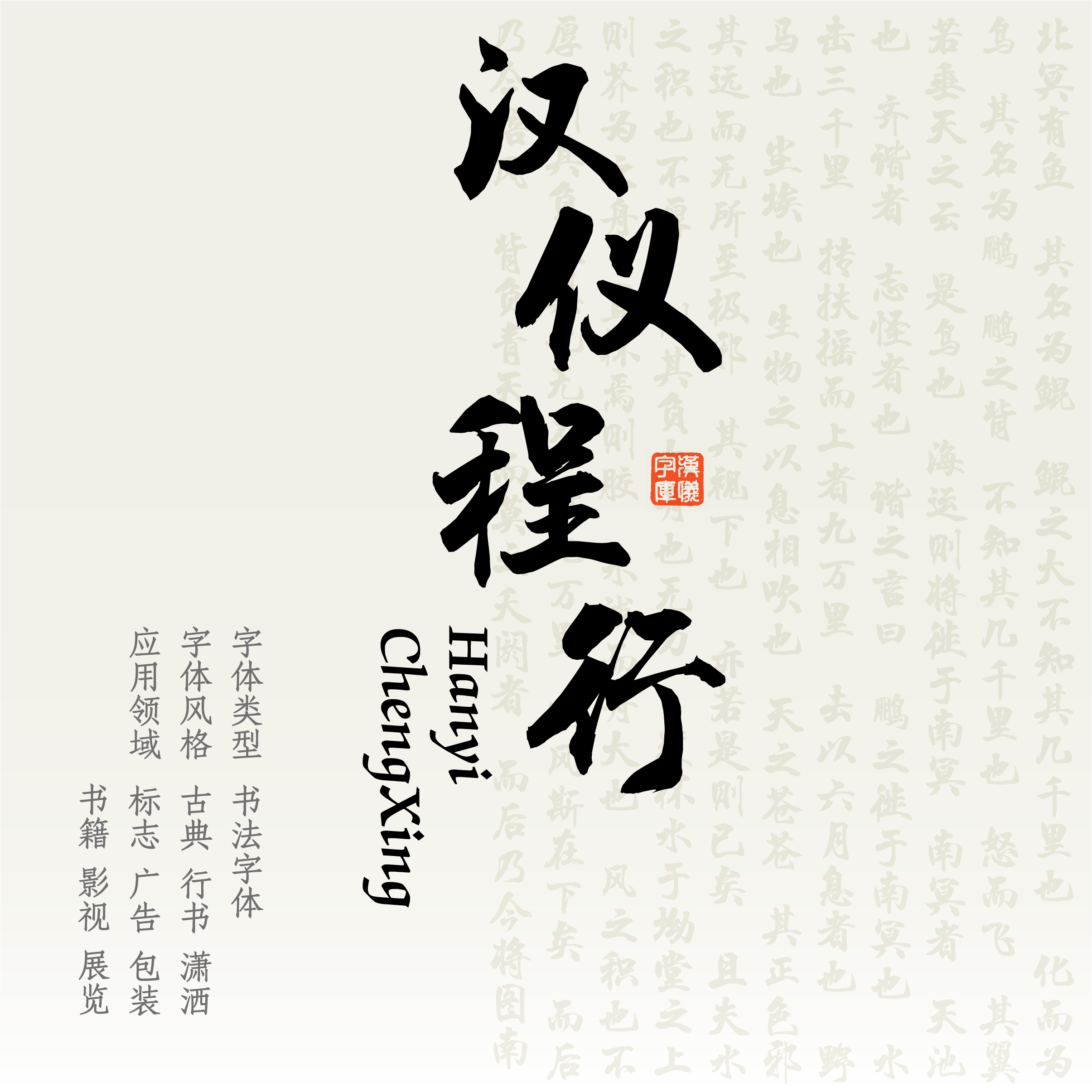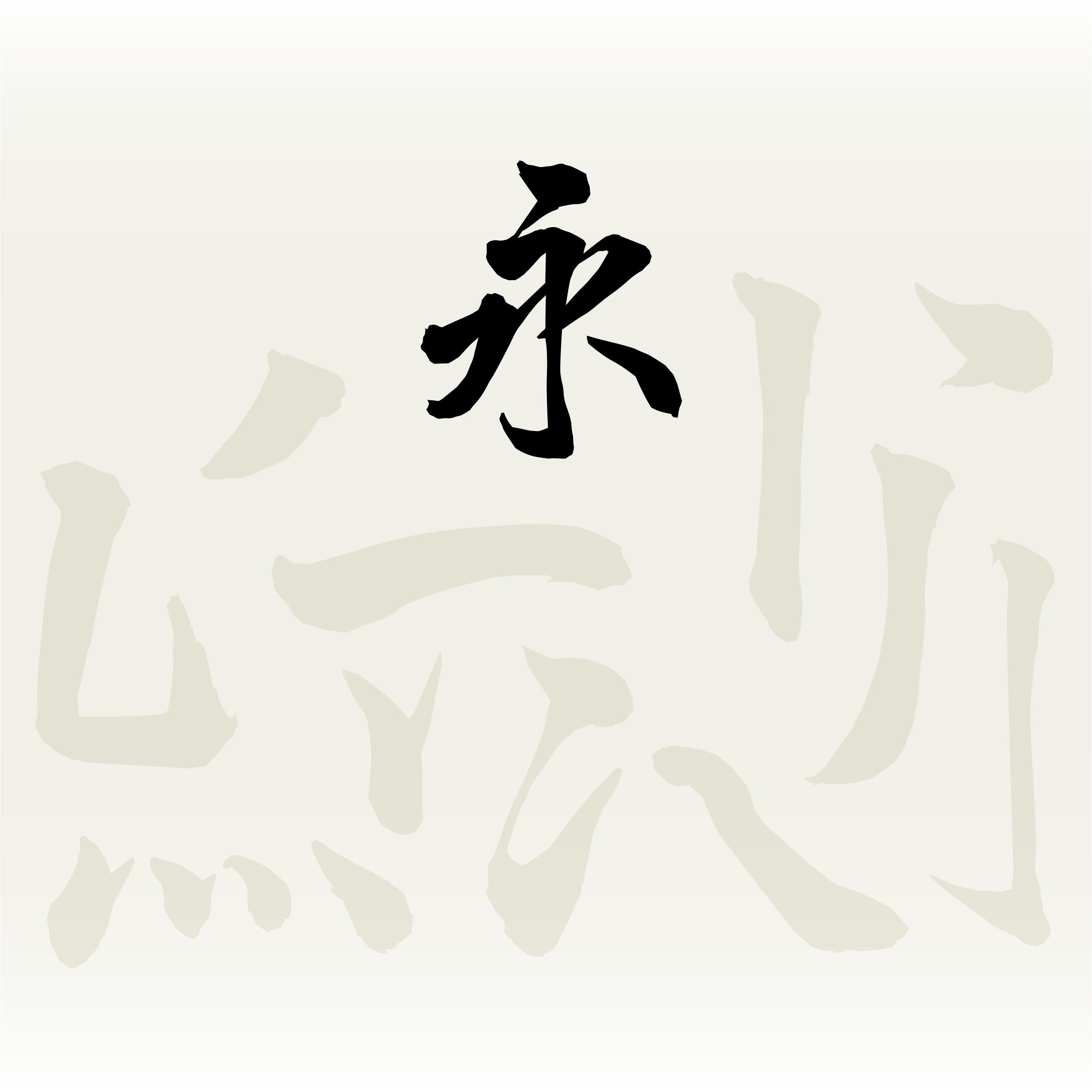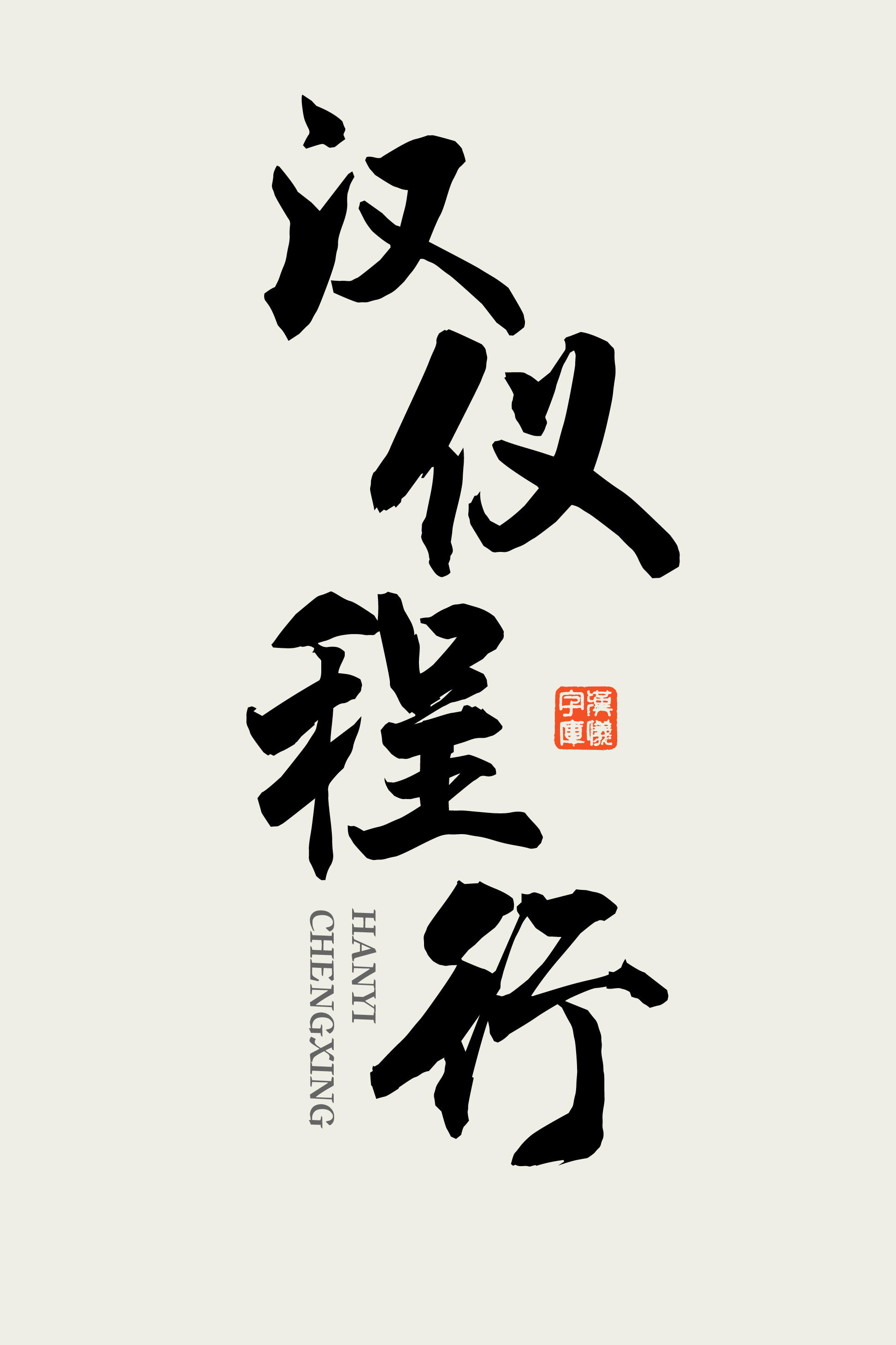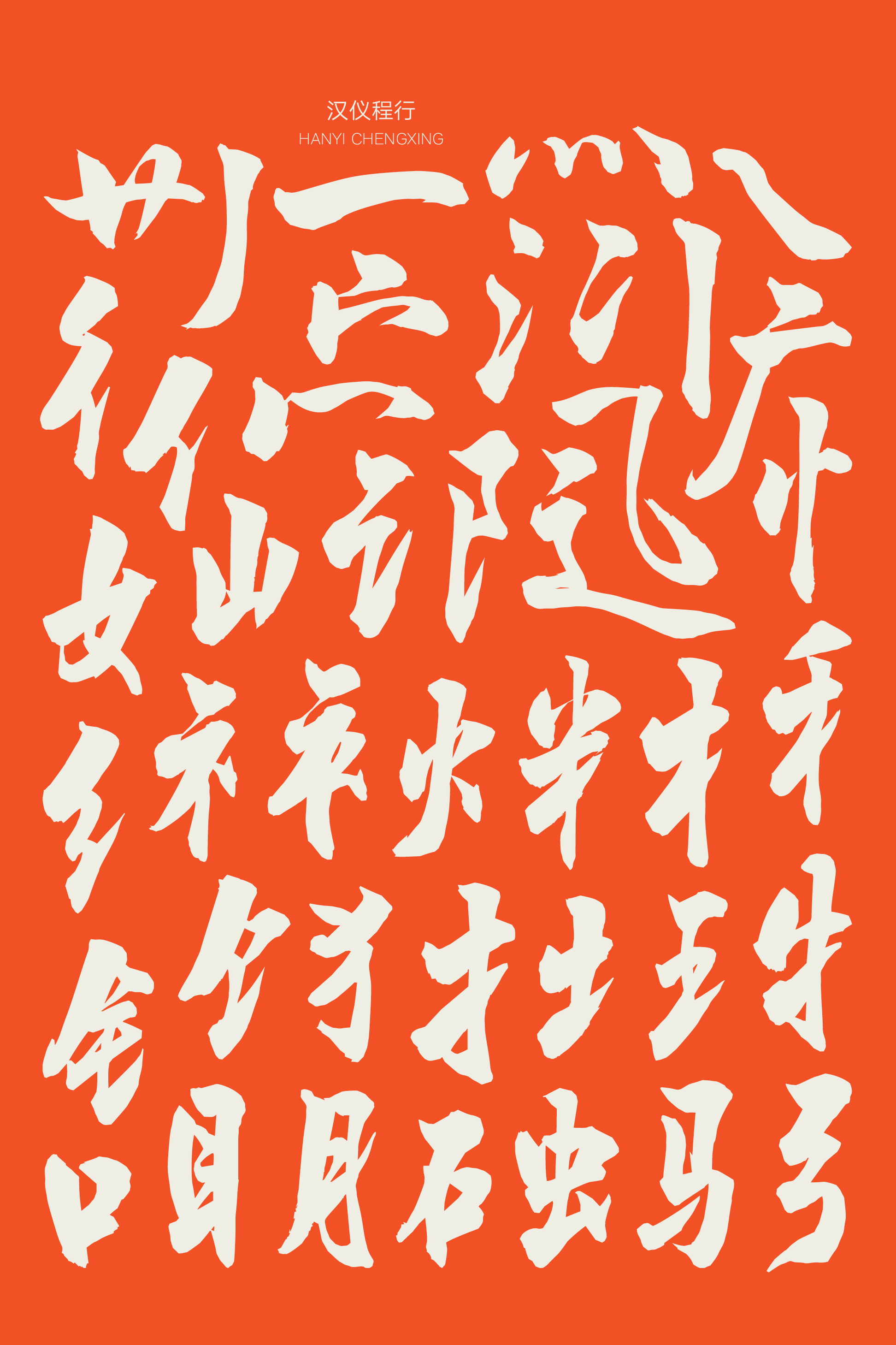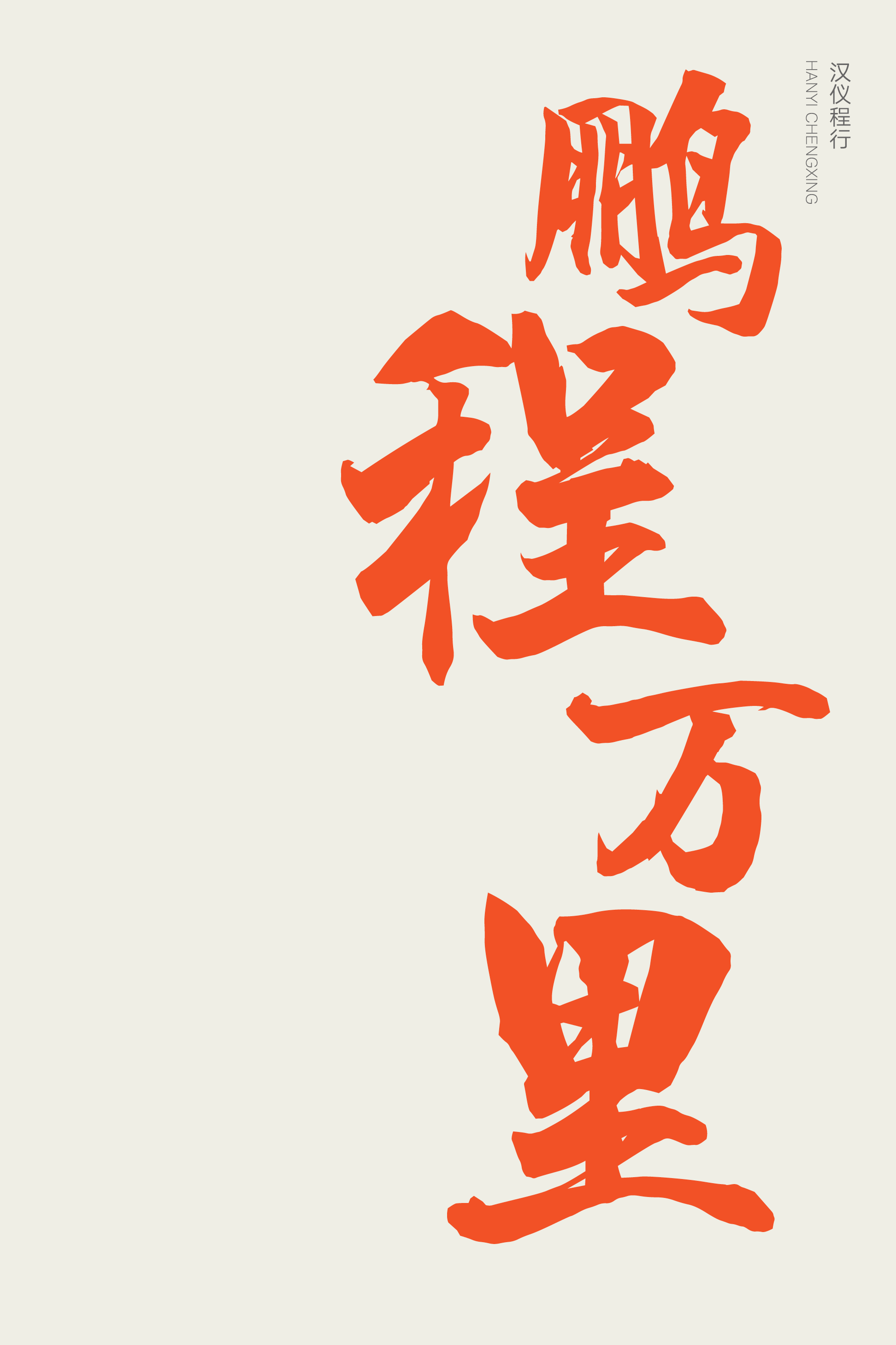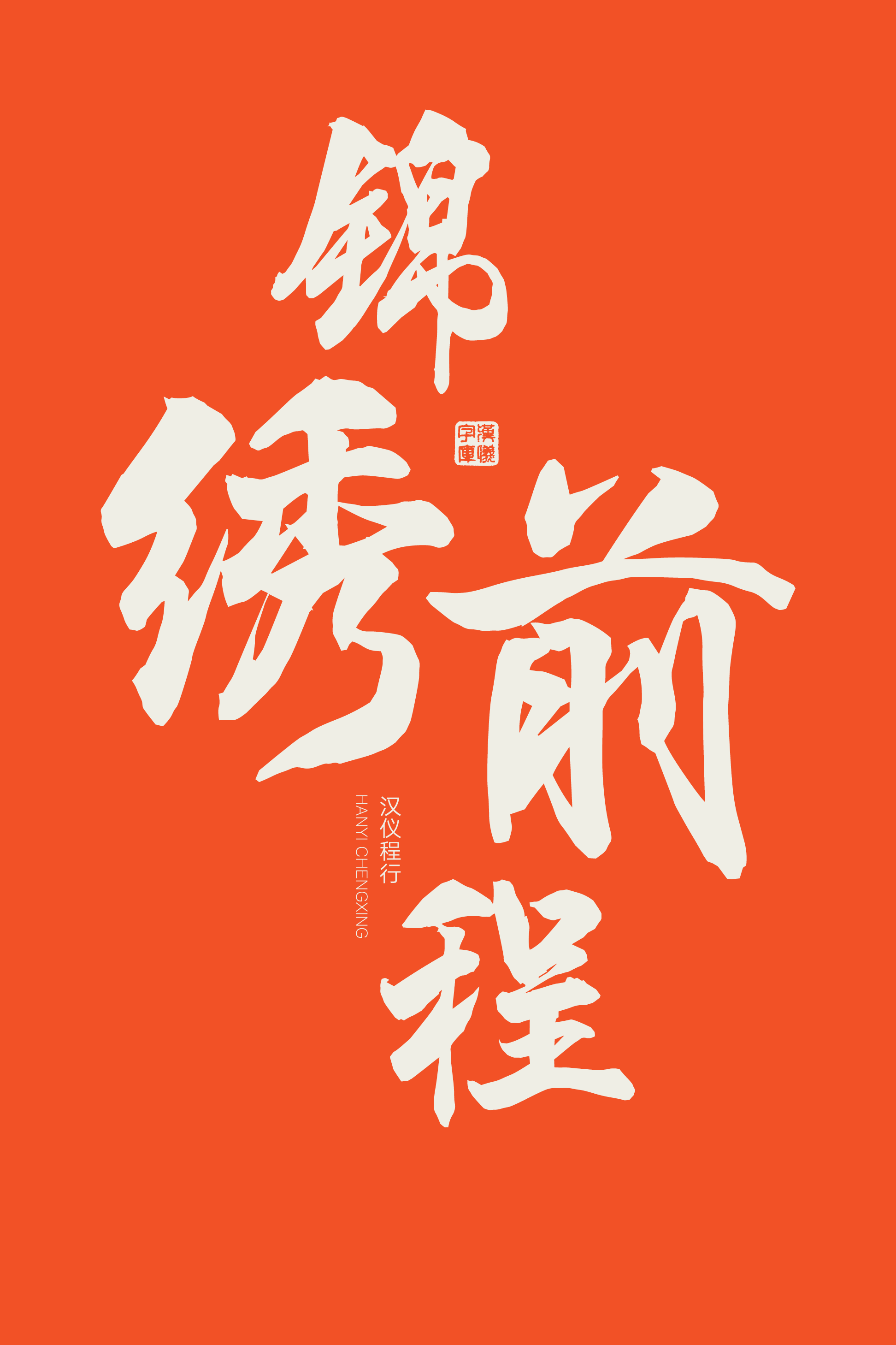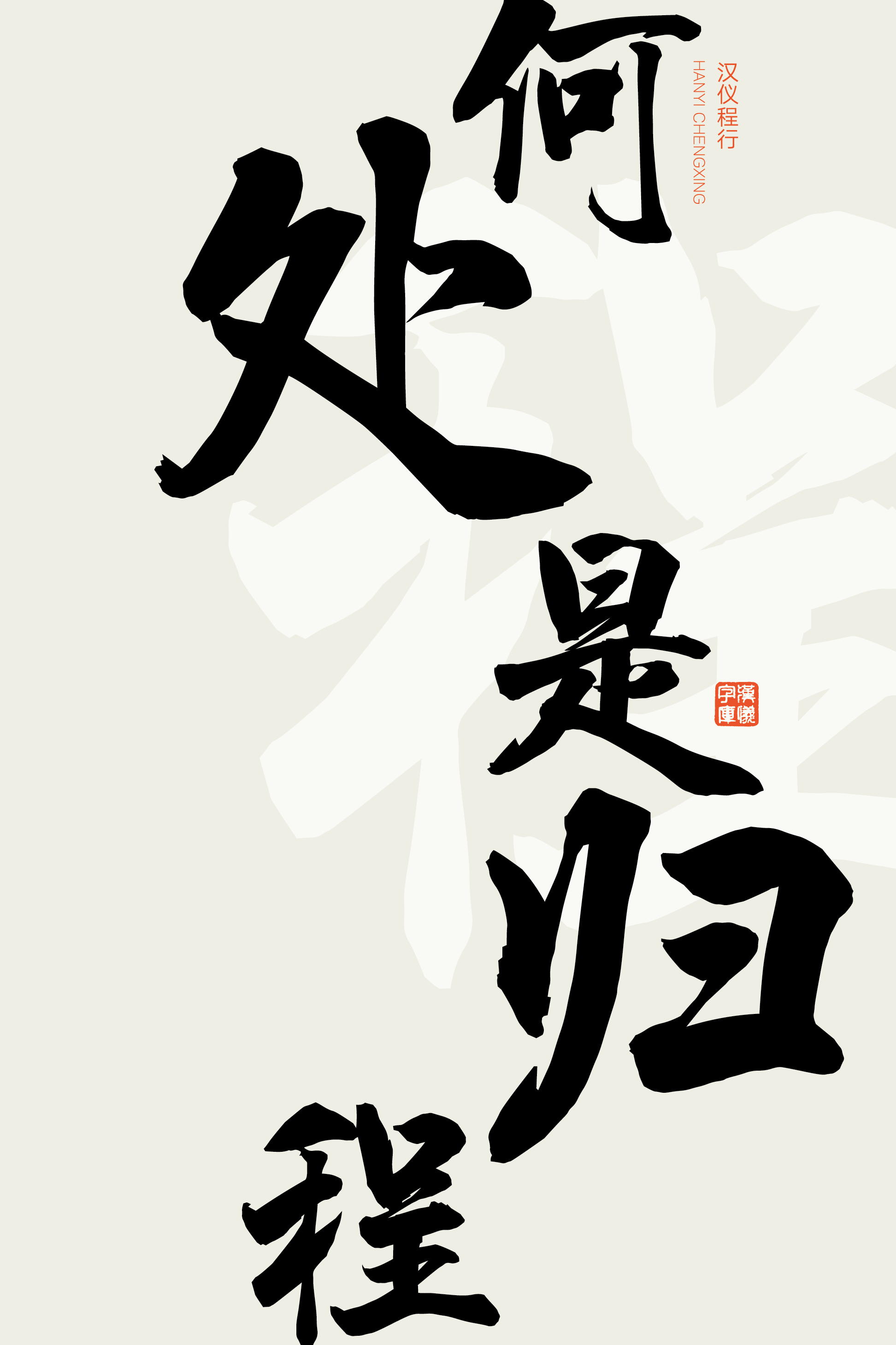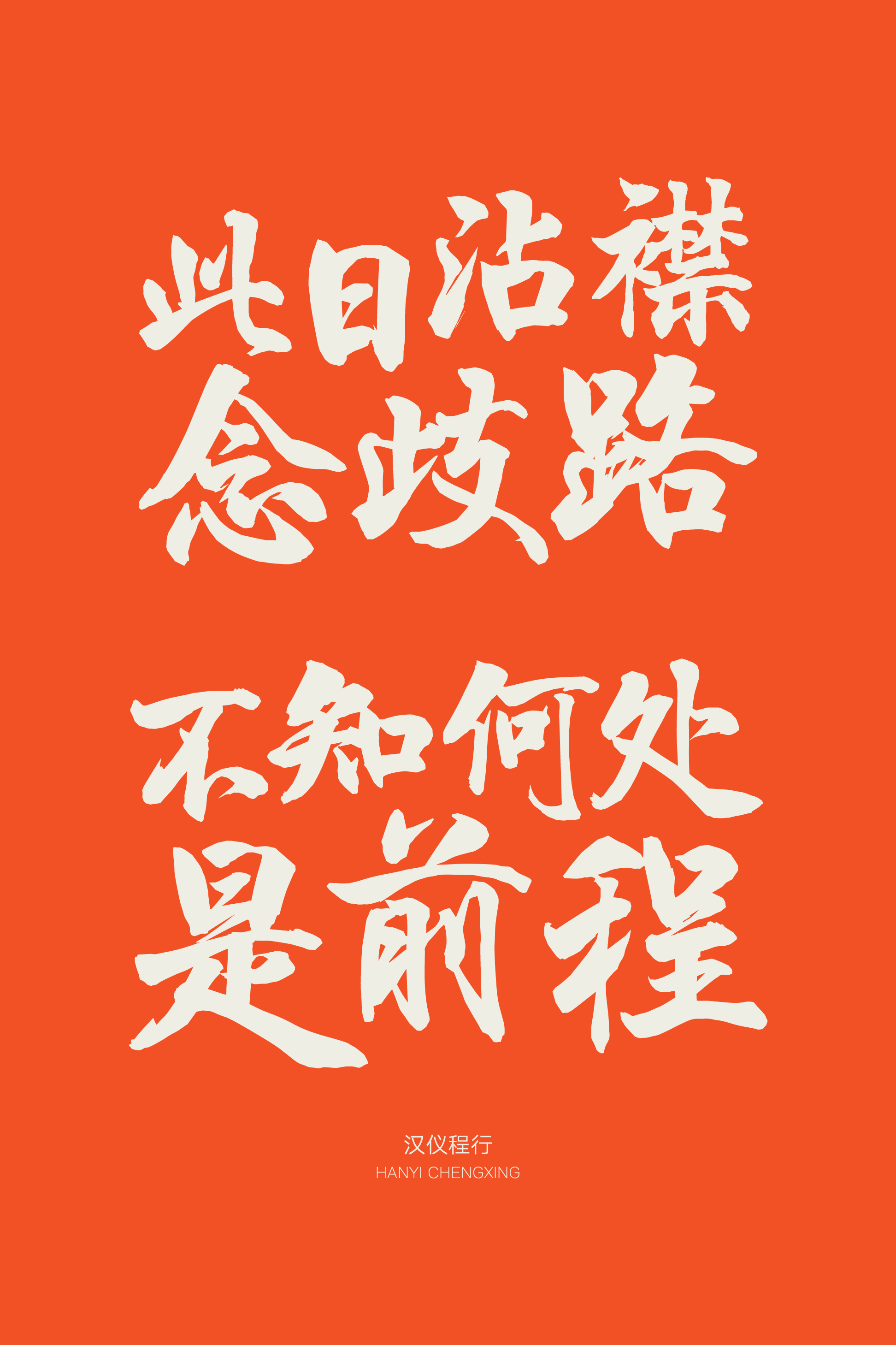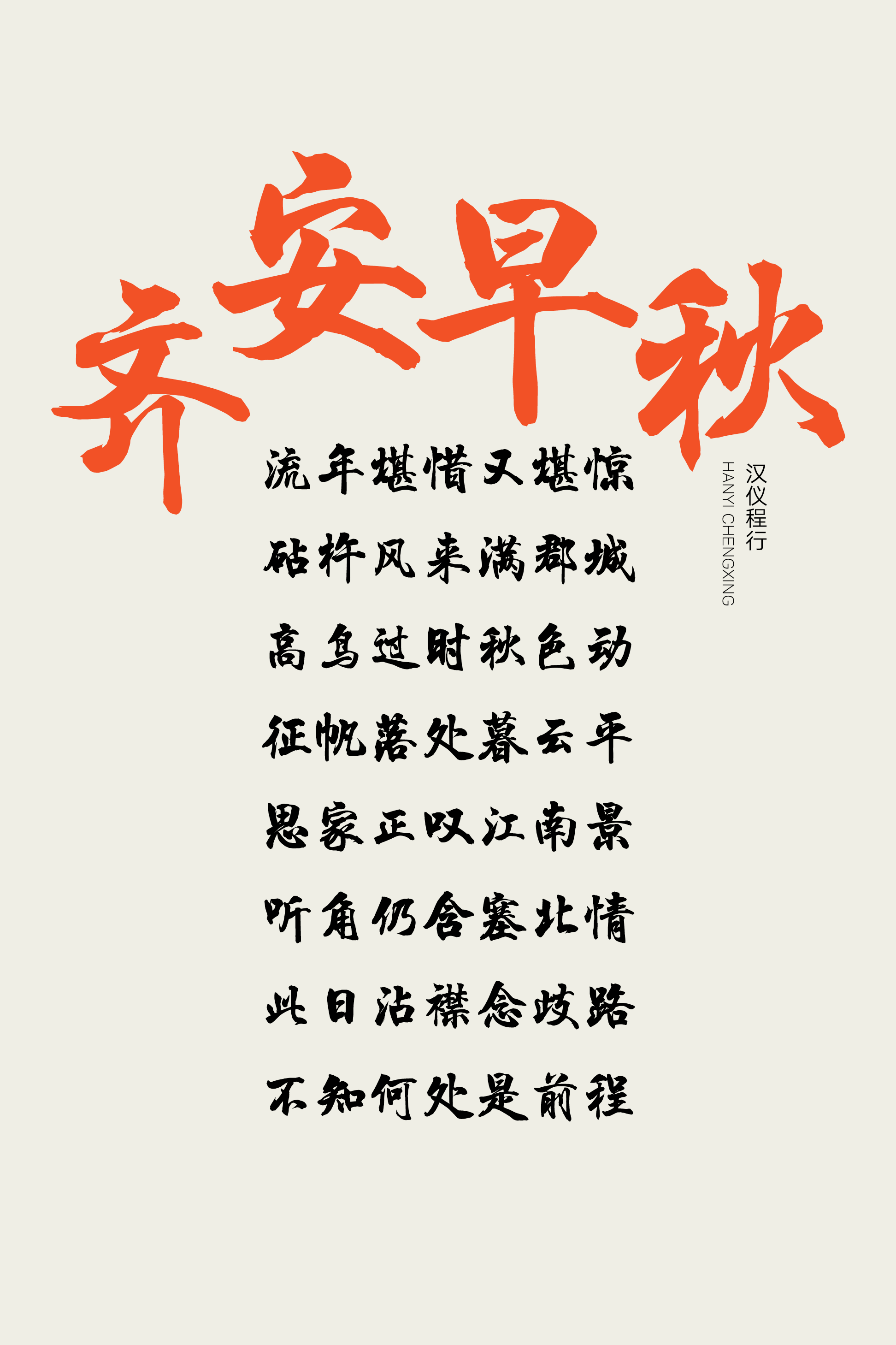
汉仪程行
汉仪程行,由著名书法家、书法教育家程似锦先生书写。在继承了传统行书的基础上,融合唐代以及魏晋风貌,不拘泥于沉规。用笔大胆,方圆兼济,雄浑沉厚,挥洒自如,张弛有度,气势磅礴。本着笔墨当随时代的精神,取“像者为古,不像为己”的个人审美取向原则,历经多年临池钻研,逐步形成了程似锦先生的个人风格。
字形端正,结体优美,重心平稳而不失韵律。
用笔大胆而潇洒,方圆兼济,雄浑沉厚。